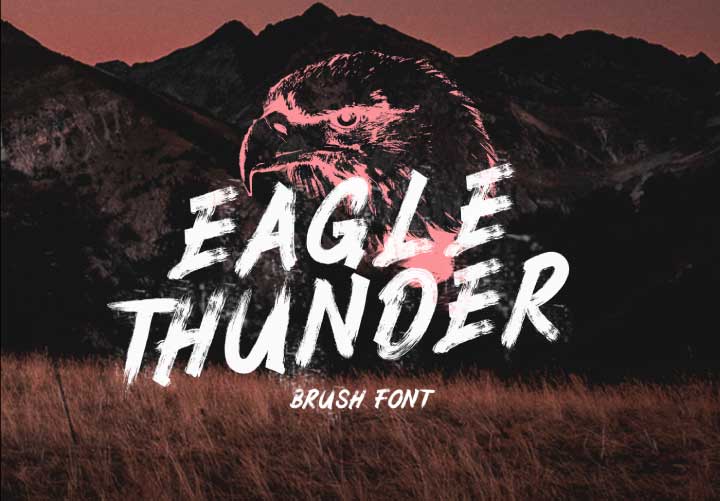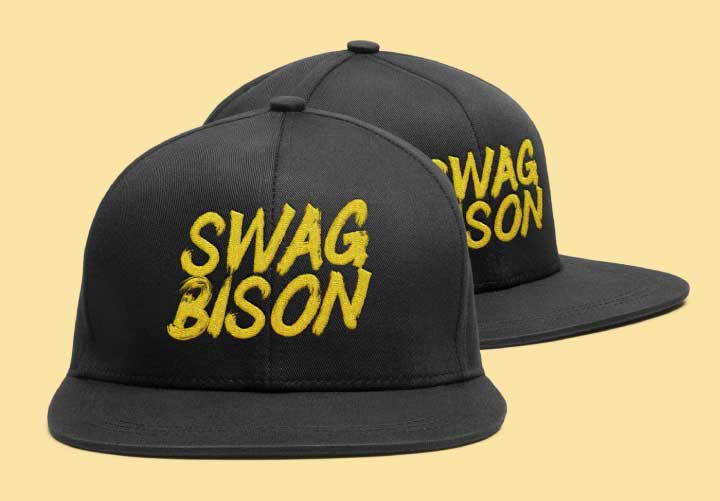
EAGLE THUNDER – Free Textured Script Font
Nama Hurufnya Eagle Thunder, dibuat oleh SEMAR not smear. Dari nama pembuatnya dipastikan kalau huruf atau font ini asli buatan anak bangsa, sekali lagi Indonesian Designer ghetoo :D. Semakin banyak kreativitas desain buatan lokal membuktikan bahwa Indonesia banyak menyimpan potensi di bidang ini.
Eagle Thunder merupakan pilihan font skrip teksur yang ideal bagi para desainer yang mencari sentuhan unik dan dramatis pada karya mereka. Font ini dirancang dengan karakter tebal dan detail tekstur yang memikat, memberikan kesan kuat dan elegan pada setiap desain.
Keunggulan Eagle Thunder terletak pada fleksibilitasnya. Font ini dapat diaplikasikan pada berbagai media dan keperluan desain, seperti:
• Desain Kemasan Produk: Memberikan daya tarik visual yang kuat pada produk, menarik perhatian konsumen.
• Desain Judul: Cocok untuk judul buku, majalah, clothing line, atau poster dengan tampilan yang mencolok.
• Branding dan Logo: Memberikan kesan profesional dan berkelas pada logo bisnis atau merek.
• Desain Kutipan: Menampilkan kutipan inspiratif dengan gaya yang artistik dan mudah diingat.
• Kartu Ucapan: Menambah sentuhan personal dan elegan pada kartu ucapan untuk berbagai acara.
Suitable for use in title design such as clothing, magazines, book titles, stationery designs, quotes, branding, logos, greeting cards, t-shirts, packaging designs, posters, snapbacks and more.